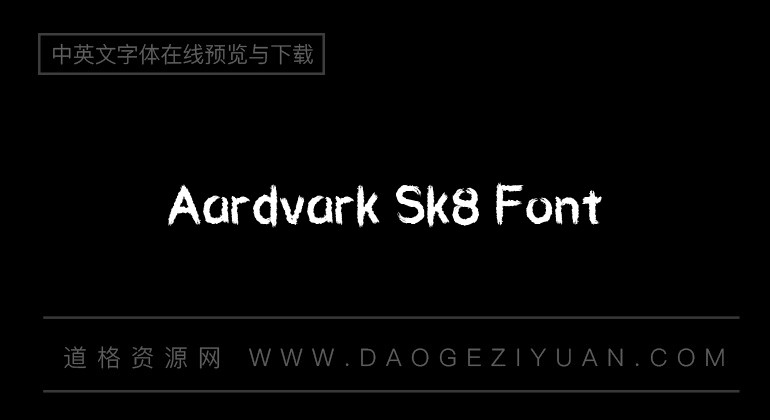
Aardvark Sk8是一种手写风格的字体,专为滑板文化而设计。该字体由Jason Naylor设计,于2017年发布。它的特点是线条弯曲自然,形态流畅,给人一种轻松、流畅、自由的感觉。该字体的每个字母都有不同的笔画宽度和角度,使得整个字体看起来非常生动有趣。 Aardvark Sk8字体适用于海报、标志、T恤、海报、包装等设计中,特别是与滑板文化相关的设计。它能够传达自由、创新、年轻、活力和个性的精神,并能够吸引年轻人的目光。内容介绍
Aardvark Sk8 Font是一款非常不错的手写艺术字体,具有很好的视觉感,适合于文化类的宣传设计、商业类品牌的广告和产品包装设计以及个性化文字排版等较多场景。